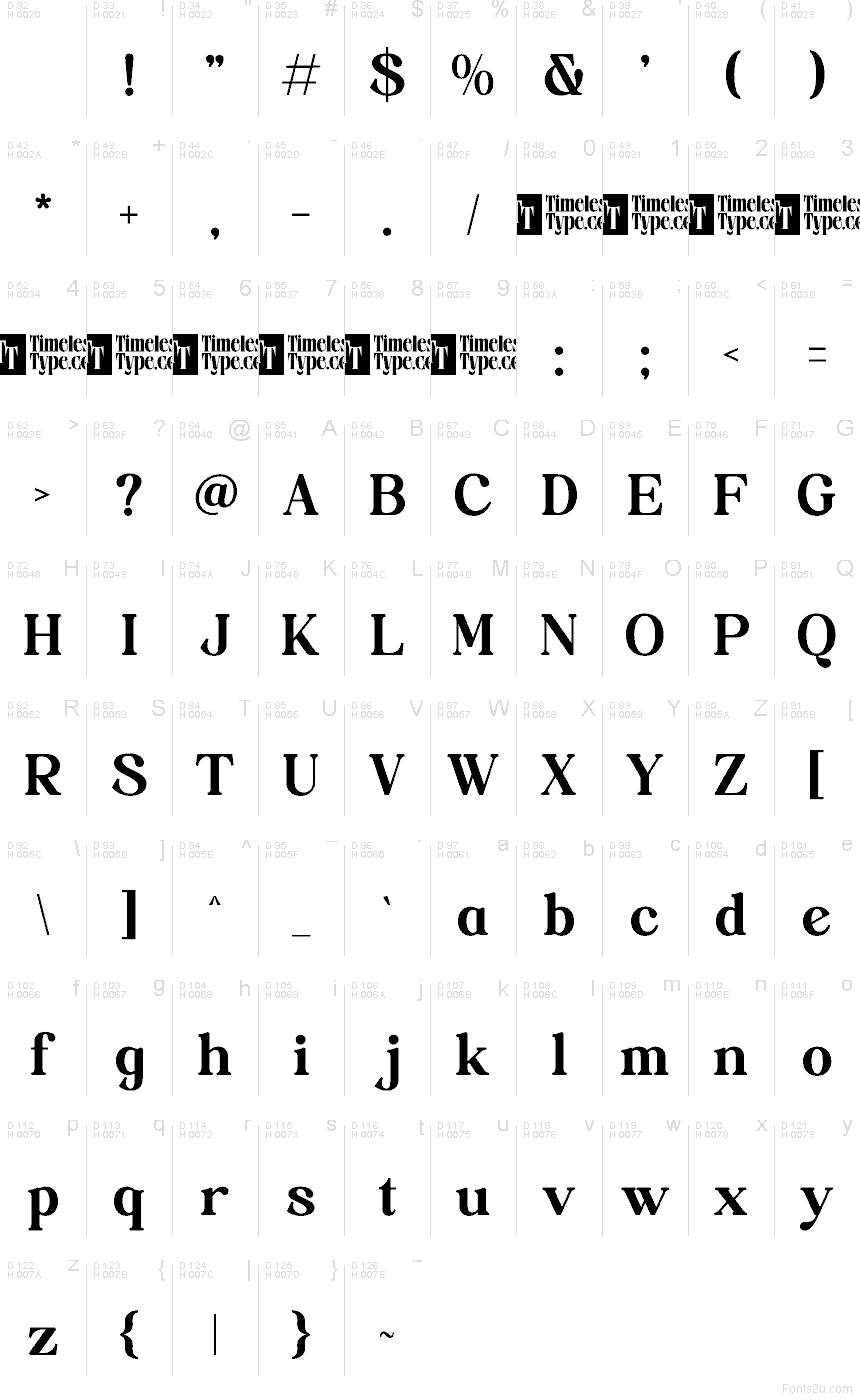
Descubra a combinação perfeita de nostalgia e elegância contemporânea com Font Builds Haven - Groovy Serif Display Font Serif Display. Esta excepcional fonte display redefine o apelo visual por meio de traços marcantes de alto contraste e cativantes serifas groovy. Unindo com maestria o charme vintage à sofisticação moderna, ela garante que suas criações atraiam a atenção de imediato e deixem uma impressão duradoura.
Alcance uma liberdade criativa incomparável com Font Builds Haven - Groovy Serif Display Font Serif Display, que traz uma impressionante coleção de 20 ligaduras e 87 caracteres alternativos. Esses elaborados elementos de design proporcionam infinitas possibilidades para compor uma tipografia autêntica e expressiva, entregando um impacto visual marcante. Com amplo suporte multilíngue, Font Builds Haven - Groovy Serif Display Font Serif Display se adapta perfeitamente aos mercados globais, tornando-se incrivelmente versátil para projetos internacionais.
Valorize seus projetos com a estética refinada de Font Builds Haven - Groovy Serif Display Font Serif Display, ideal para uma vasta gama de aplicações de alto padrão. Ela se destaca em marcas de luxo, embalagens e design editorial, onde um toque de glamour e sofisticação é essencial. Perfeita para títulos, diagramação de revistas, rótulos de produtos premium, branding de moda e identidades visuais de boutiques, garantindo uma presença verdadeiramente memorável.